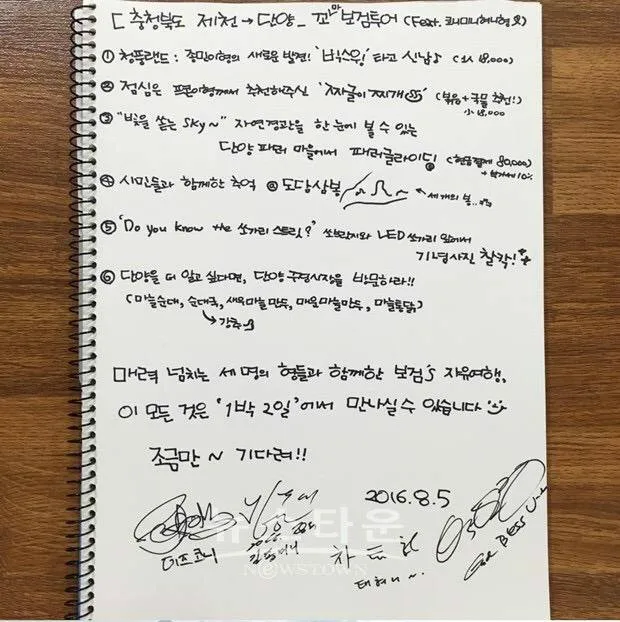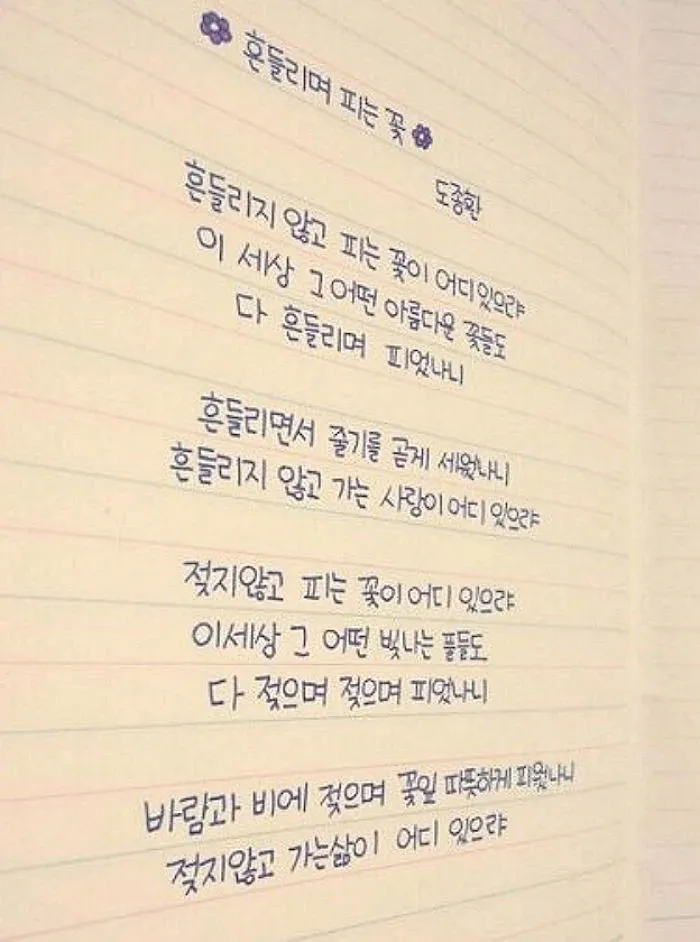
Tulisan Tangan Park Bo Gum Bagus & Rapi, Fans Berharap Untuk Dijadikan Font
Kapanlagi.com - Park Bo Gum sepertinya merupakan sosok yang akan terus membuat penggemar jatuh hati. Kali ini sang aktor mencuri perhatian karena tulisan tangannya yang diketahui begiu bagus dan rapi.
Dalam sebuah komunitas online, mereka memposting sederetan bukti tulisan tangan Park Bo Gum. Benar-benar seperti yang ditulis oleh para netizen, bintang 24 tahun ini memang punya tulisan tangan yang indah.
Tulisan tangan Park Bo Gum yang mendapat pujian dari netizen. © koreaboo.comBahkan nggak sedikit yang merasa kalau tulisan tangan Park Bo Gum ini mirip dengan font di komputer loh. Penggemar juga meninggalkan komentar mereka berharap tulisan tangan bintang REPLY 1988 dan MOONLIGHT DRAWN BY CLOUDS tersebut untuk dijadikan font.
"Tolong tulisan tangan ini dibuat font", "Dia bahkan juga menulis dengan baik", "Tulisan tangannya begitu cantik", dan "ini benar-benar sempurna," tulis sederetan netizen seperti yang dilansir Koreaboo.
Coret-coret di buku catatan Park Bo Gum. © koreaboo.comBahkan coret-coretan di buku Park Bo Gum juga memperlihatkan tulisan tangan yang bagus meski loh. Penggemar pun memuji betapa cocok tulisan tangan idolanya ini dengan kepribadian yang dimiliki.